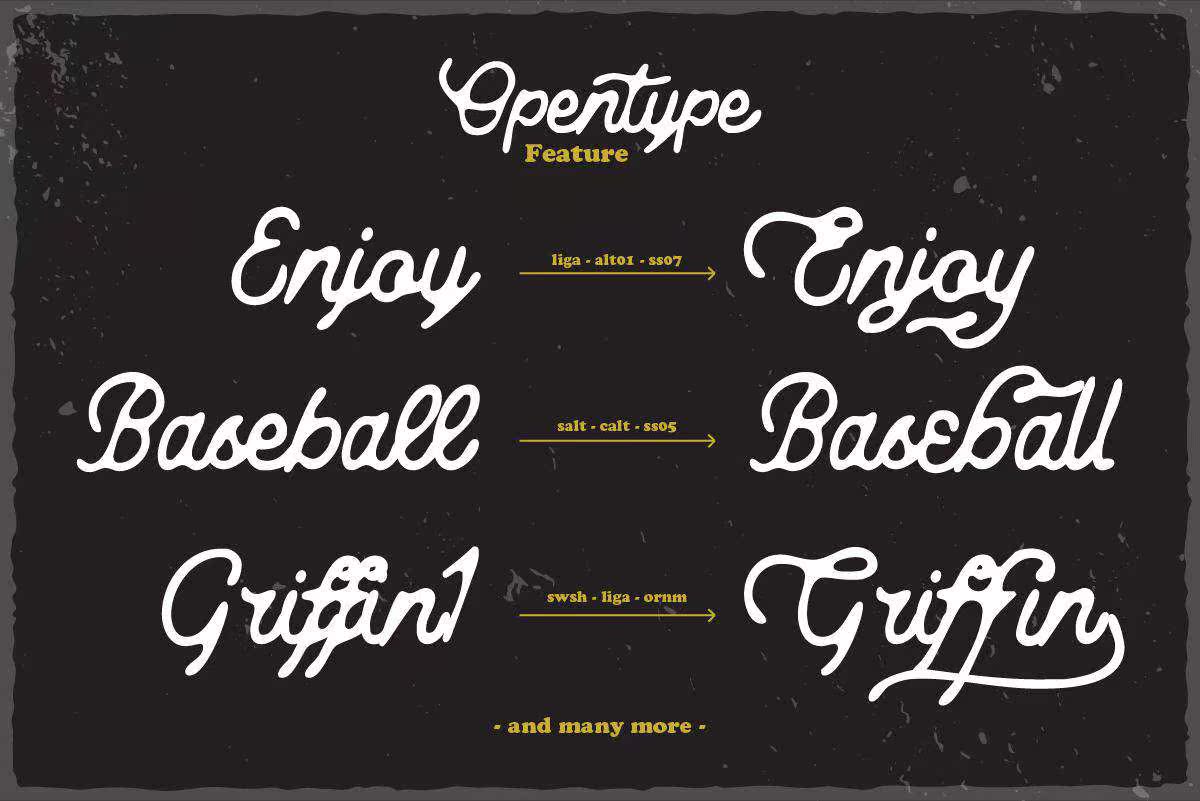
AltobelloScript是一款具有挤出(阴影)功能的脚本,可在创建阴影效果时节省您的时间。它可用于不同的场景:文字和日志类型、标签、t恤、产品包装、邀请、,广告和文字索引设计。AltobelloScript是一种具有挤出(阴影)功能的脚本,可在创建阴影效果时节省时间。它可用于不同的场景:文字和文字、标签、t恤、产品包装、邀请、广告和文字索引设计。